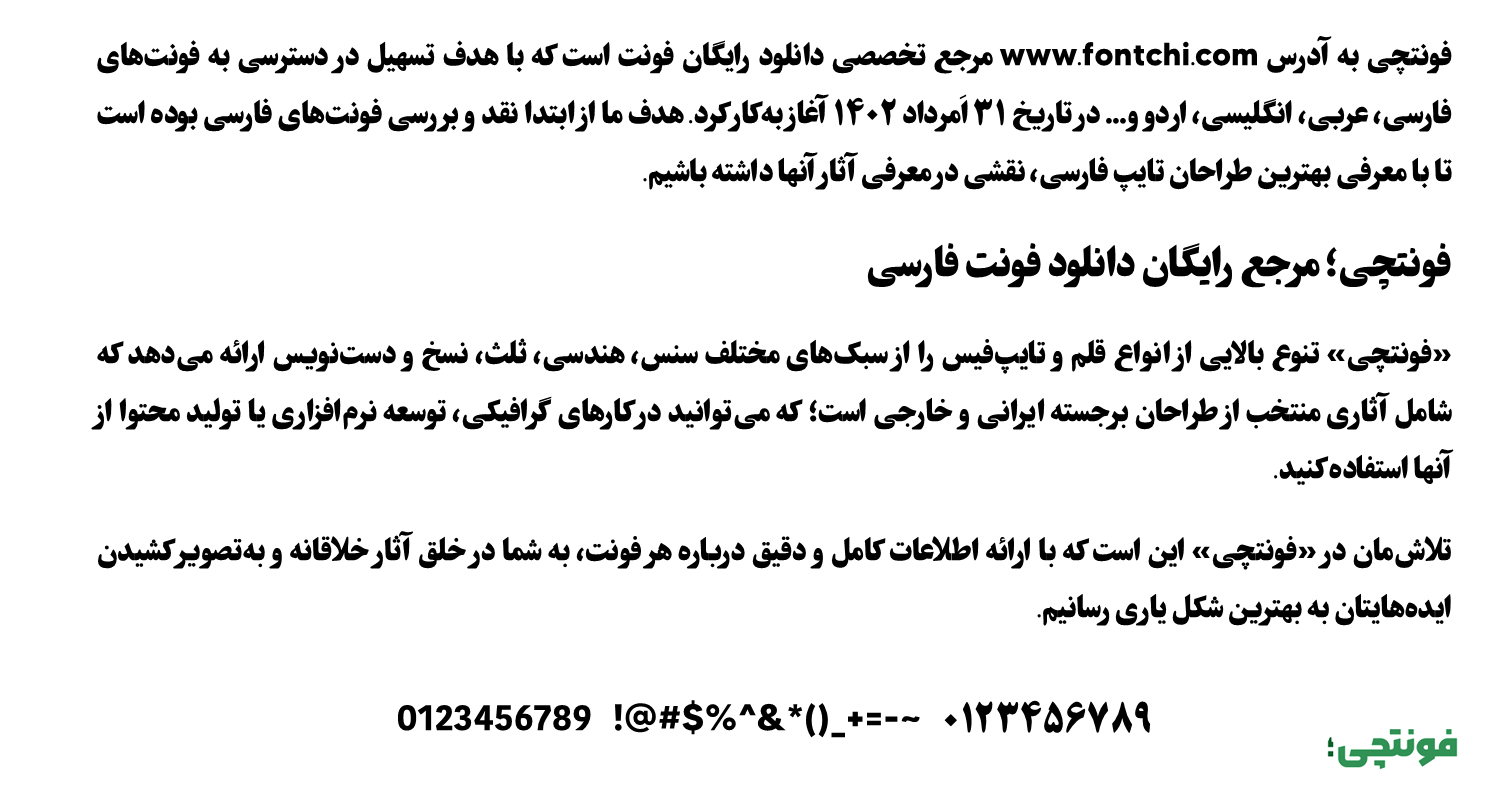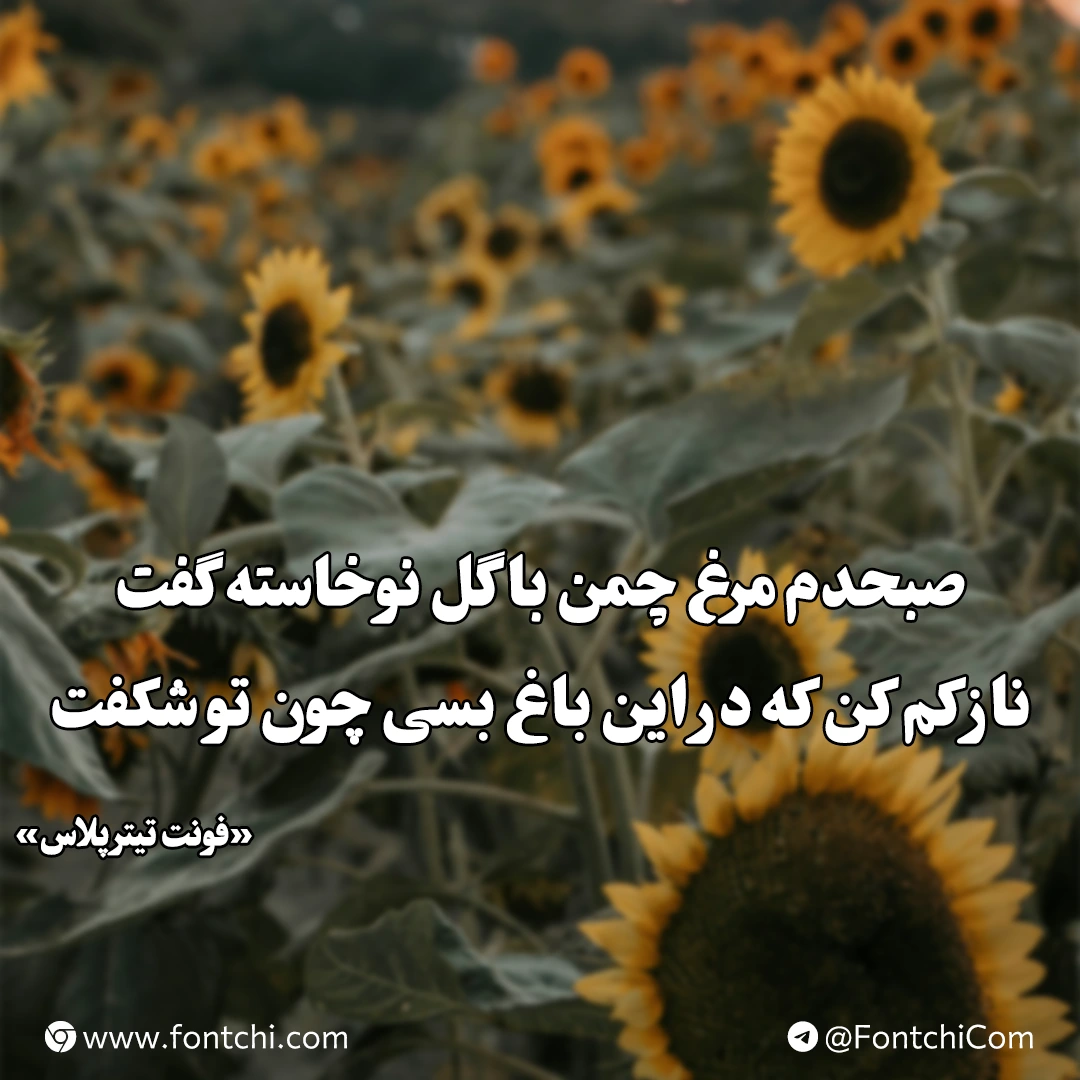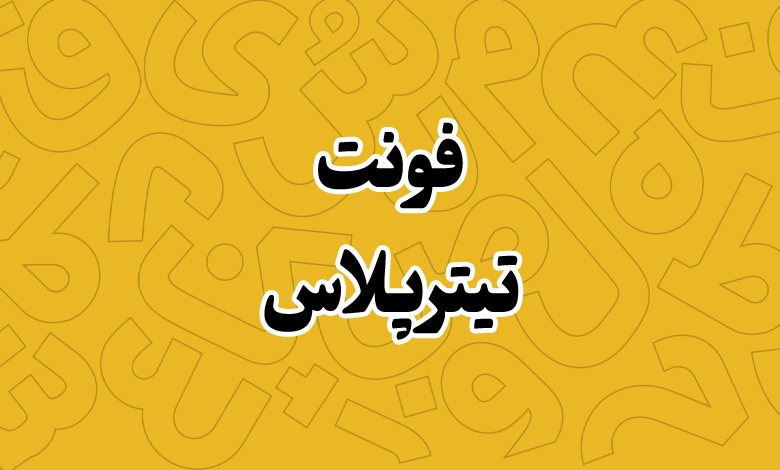
فونت تیتر پلاس (Titr Plus)
فونت تیتر پلاس (به انگلیسی: Titr Plus) یکی دیگر از فونتهای آزاد طراحی شده بر پایه فونت تیتر است که میتوانید از آن در پروژههایی که نیازمند فونت عنوان و نمایشی هستید استفاده کنید. در ادامه با بررسی و دانلود فونت تیتر پلاس با شما همراه هستیم.
فونت دیجی تیتر پلاس توسط مهدی برقگیر طراحی شده است که از ۳ سبک نقطهگذاری با یک وزن بولد پشتیبانی میکند. در تصویر زیر بهترتیب هر سه سبک نقطه گرد، نقطه چسبان و نقطه مربعی را مشاهده میکنید.
فونت فارسی تیتر پلاس از زبان فارسی پشتیبانی کاملی دارد و با توجه به اینکه بر اساس فونت تیتر طراحی شده است اصلاحات متعددی از نظر اعرابگذاری، فواصل و کرگینگ بر روی تمامی حروف اعمل شده است. این فونت همچنین از زبان عربی پشتیبانی کاملی دارد که میتوانید در پروژههای چند زبانه از آن استفاده کنید.
گلیفهای حروف در این فونت به شکل استاندارد طراحی شده که شامل تمامی حروف متفاوت عربی مانند «ک، ی، ه، ؤ، ئ» و اعداد «۴۵۶» است. فونت Titr Plus از یک وزن بولد پشتیبانی میکند که در ۳ نسخه متفاوت در بخش نقطهگذاری ارائه شده است. البته هر سبک در قالب فایل جداگانه ارائه شده است.
- Digi Titr Plus Bold Line: خطی چسبان
- Digi Titr Plus Bold Circle: نقطه گرد
- Digi Titr Plus Bold Rectangle: نقطه مربعی
از این فونت با توجه به سبکی که در نقطهگذاری و وزن بولد دارد، میتوانید در پروژههایی با متون کوتاه، بهویژه در عناوین استفاده کنید. محیطهای تبلیغاتی، عناوین و حوزه چاپ بیشترین کاربرد را برای این قلم دارند. همچنین در شبکههای اجتماعی نیز میتوانید به عنوان فونت رایگان اینشات فارسی از این قلم برای طراحی تصاویر و کاورهای خود استفاده کنید.